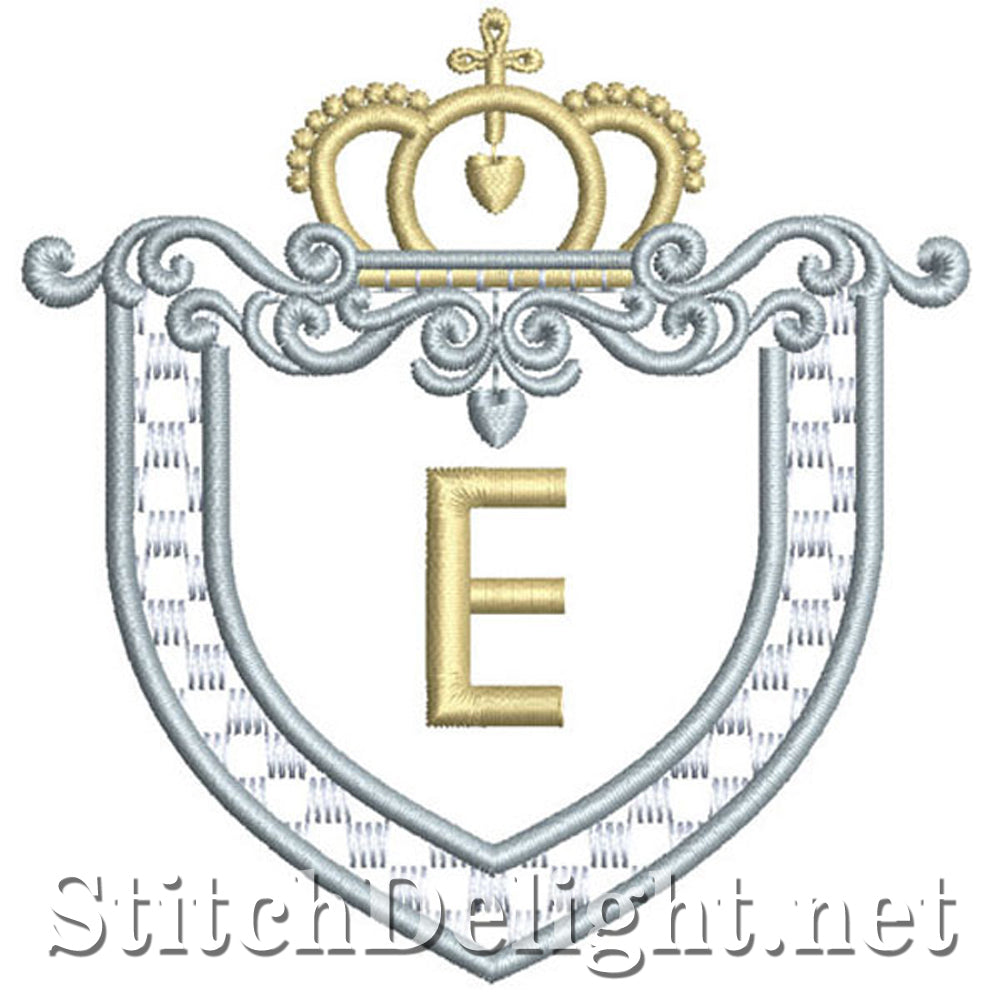
SDS1178 Royal Frame-lettertype E
Prachtig lettertype geschikt voor royalty's, dit lettertype is prachtig op linnen - het bevat een blanco lijst zodat je je eigen ontwerp of belettering in het midden kunt toevoegen - Grootte van het frame is 3,71x33,89", aantal steken ongeveer 7900 steken - De letters die ik heb gebruikt, is het nieuwe steekopvultype genaamd Raised Satin, dat het schuimborduurwerk nabootst, dus het komt meer uit de stof dan andere steken, geen schuim nodig